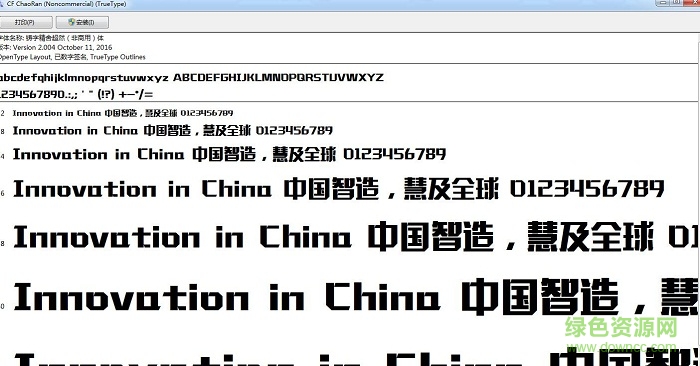
鑄字精舍超然體w
鑄字精舍超然體是一款大氣好看的中文字體,筆畫堅(jiān)毅,橫粗豎細(xì),線條利落,十分有型,喜歡這款字體的小伙伴趕緊來綠色資源網(wǎng)下載吧!
鑄字精舍超然體特點(diǎn)
該字體線條比較粗壯,字形端正大方得體,整體效果非常的出眾,并且字庫完整,可用于藝術(shù)設(shè)計(jì)、包裝印刷、簽名設(shè)計(jì)、圖形設(shè)計(jì)等領(lǐng)域!